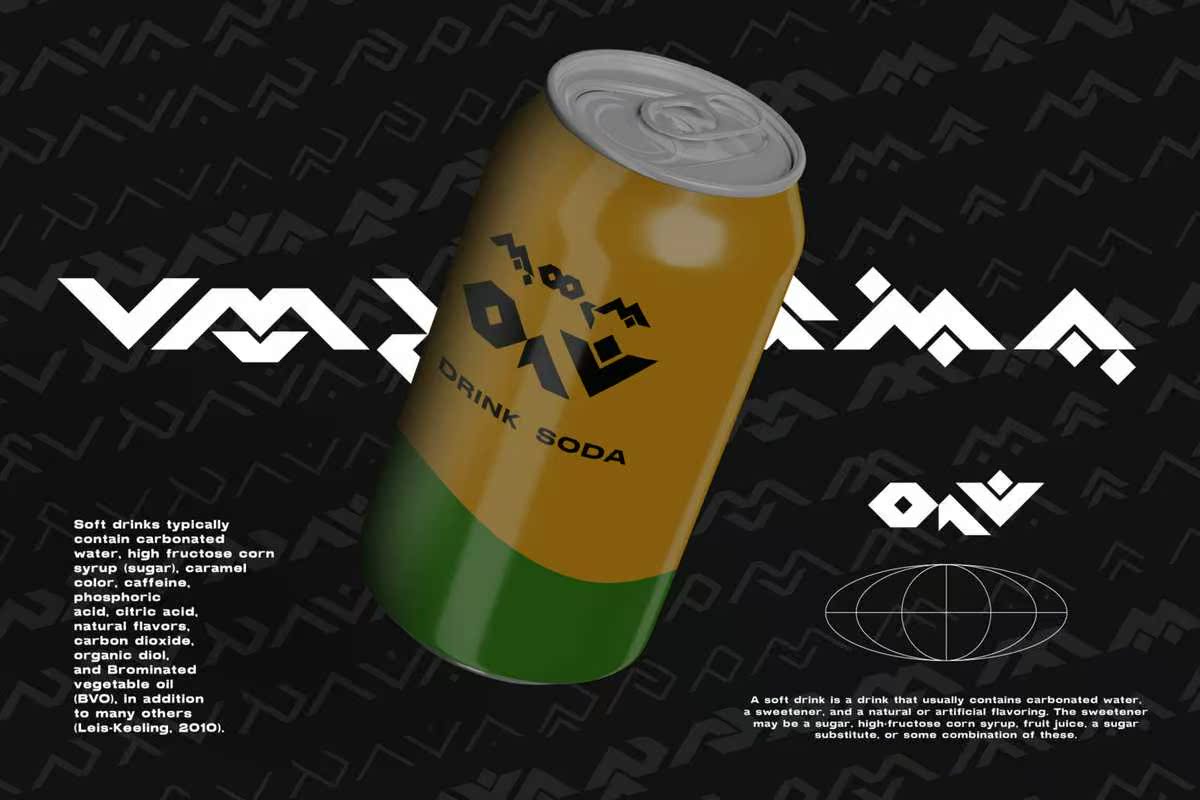
NEUELONTARA。传统的Makassar语言与其他地区语言相同这本书的存在对当地社区来说是无益的,因为有上百种地区语言在印度尼西亚,不允许他们具有喀什玛萨社区的特征。本说明适用于Saksaralontara.NEUELONTARA。传统的Makassar语言是该地区语言的新语言这本书的存在对当地社区来说是无益的,因为有上百种地区语言在印度尼西亚,不允许他们具有萨卡萨社区的特征。本说明适用于Saksaralontara。